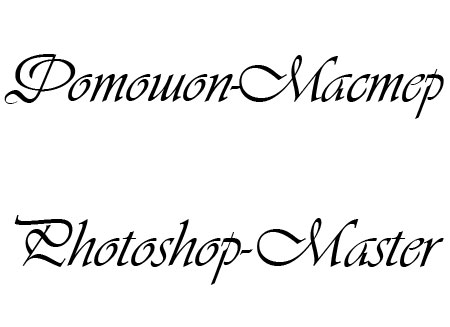
Он ужасен. А "Красивость" выражается большим использованием на витринах? Собственно, и забрела на этот сайт, чтобы скачать это убожество (для проекта плохих шрифтов надо!).
Не русифицирован.
Браво автору, это что-то филигранное и превосходное, очень тонко всё и невероятно изящно!
Он ужасен. А "Красивость" выражается большим использованием на витринах? Собственно, и забрела на этот сайт, чтобы скачать это убожество (для проекта плохих шрифтов надо!).
красиво!
Красивый шрифт!)
Красиво...)